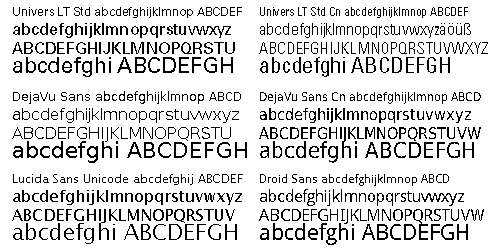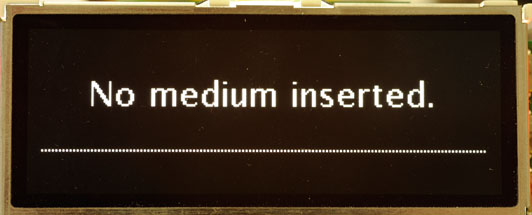
Frage zu Bitmap-Font für Monochrome-Display
Unsere Firma ist gerade dabei, für einen Kunden (Autohersteller) eine Bedienoberfläche für ein Entertainment-System zu erstellen. Das System hat ein Monochrome-Display (wirklich nur schwarz und weiß, keine Zwischenstufen) mit einer Auflösung von 250px × 78px (Größe ca. 10,6cm × 3,3cm).
Wir überlegen, zwei oder drei verschiedene Schriftgrößen einzusetzen, und sind nun auf der Suche nach einem geeigneten Bitmap-Font, der sich auch in reiner S/W-Darstellung gut lesen läßt.
Hier gibt es natürlich mehrere Möglichkeiten:
• einen Font in verschiedenen Größen from scratch neu entwickeln
• bereits existierende Bitmap-Fonts verwenden
• die Buchstaben eines Vektorfonts als einzelne Bitmaps rendern
Aufgrund der Tatsache, daß viele Sprachen unterstützt werden sollen, ist mit einem großen Zeichenvorrat zu rechnen. Bei einem ähnlichen Projekt hat der Kunde selbst einen Font mit 425 Zeichen zugeliefert. Ok, ein paar davon enthielten auch Konstrukte wie »km/h« oder »mi/gal«, die irgendwo in der Bedienoberfläche verwendet wurden.
Nun meine Fragen:
• Gibt es qualitativ hochwertige, aber kostenlose Bitmap-Fonts mit hoher Zeichenabdeckung, die für kommerzielle Zwecke eingesetzt werden dürfen?
• Sind die Lizenz-Bedingungen bei Bitmap-Fonts ähnlich wie bei Vektor-Fonts? (Schließlich gibt es bei Bitmap-Fonts, z.B. für die Größe 5 × 7, nur eine begrenzte Anzahl von verschiedenen Möglichkeiten, sagen wir mal ein »M« darzustellen. Kann es darauf dann ein Copyright geben?)
• Wenn jemand, der eine Lizenz für einen Vektor-Font besitzt, aus diesem dann einen Bitmap-Font generiert: Darf dieser Bitmap-Font dann ohne weitere Lizenzen in einem Produkt eingesetzt werden?
Bei 4 Textzeilen bzw. auch Listendarstellung mit vier Zeilen auf dem oben beschriebenen Display bleiben für jede Zeile brutto knapp 20px übrig. Denkbar wären Fonts in den Größen 22px, 16px und 12px.
Da Screens für verschiedene Anwendungen benötigt werden (Radio, Media Player, Telefon), kann es durchaus sinnvoll sein, für verschieden wichtige Informationen verschieden große Schriften zu verwenden; wichtig ist natürlich, daß die kleinen Schriften noch entzifferbar sind. Natürlich gibt es auch vergleichbare Systeme, die mit einer einzigen Schriftgröße »auskommen« …
Habe mal testweise die Lucida Sans Unicode in 19px in Photoshop gerendert und die 100 wichtigsten Zeichen als BMPs abgespeichert. Das sieht gar nicht mal so schlecht aus (wahrscheinlich gutes Hinting), aber mir stellt sich immer noch die Frage nach den Lizenzen.
Hast du das auch mal mit den DejaVu-Schriften versucht? Wenigstens gäbe es da kein Lizenzproblem.
Ich habe mal eine Vergleichs-Bitmap angelegt mit Proben der Fonts Univers, DejaVu Sans, Lucida Sans Unicode und Droid Sans, jeweils in 12px, 16px und 22px.
Bis auf die Univers scheinen alle Fonts mehr als ausreichend gut ausgebaut zu sein.
Aber das Bild zeigt, wie unterschiedlich gut die verschiedenen Fonts für diesen Zweck geeignet sind.
Da eine nicht ganz so große Laufweite der Schrift bei kleinen Displays generell nicht schaden kann, hab ich auch von der Univers und der DejaVu mal die Condensed-Versionen mit hinzugenommen. Leider mit keinem guten Ergebnis.
Eigentlich ist es wirklich naheliegend, erstmal die Hausschrift des Kunden anzutesten, obwohl ich zugegebenermaßen die Idee nicht hatte. Aber wäre es nicht auch ein gewisser Zufall, wenn ausgerechnet die Hausschrift in z.B. 12px schwarzweiß in ordentlicher Qualtität und gut lesbar gerendert würde? Da gibt es doch bestimmt Fonts, die speziell für diesen Zweck optimiert wurden … Und die Hausschrift wurde vom Kunden bestimmt nach anderen Kriterien ausgewählt. Aber wenn's passen würde, wär's natürlich cool.
Achja, und außerdem muß die Schrift natürlich mit der Swiss 721 BT zusammenpassen, in der die Knöpfe der Bedienfront beschriftet sind … :lol:
Vielleicht ergibt sich ja noch die eine oder andere Idee …
Achja, und außerdem muß die Schrift natürlich mit der Swiss 721 BT zusammenpassen, in der die Knöpfe der Bedienfront beschriftet sind … :lol:
Hm, theoretisch wäre es ja angenehm, wenn sich Aufdrucke und Displayschrift möglichst ähneln ... Wobei die Helvetica jetzt nicht unbedingt ein Meisterwerk der Lesbarkeit ist ... Dafür sollte es nicht schwer sein, einen freien Klon aufzutreiben, vielleicht gibts sogar nen freien Bitmap-Klon ...
Das wäre in der Verantwortung des Typedesigners. Es muss lediglich der grobe Rahmen vorgegeben werden: Westeuropa, Zentraleuropa (Tschechisch etc.), Russisch, Griechisch etc.
Also ich finde, das sieht jetzt nicht so schlecht aus …